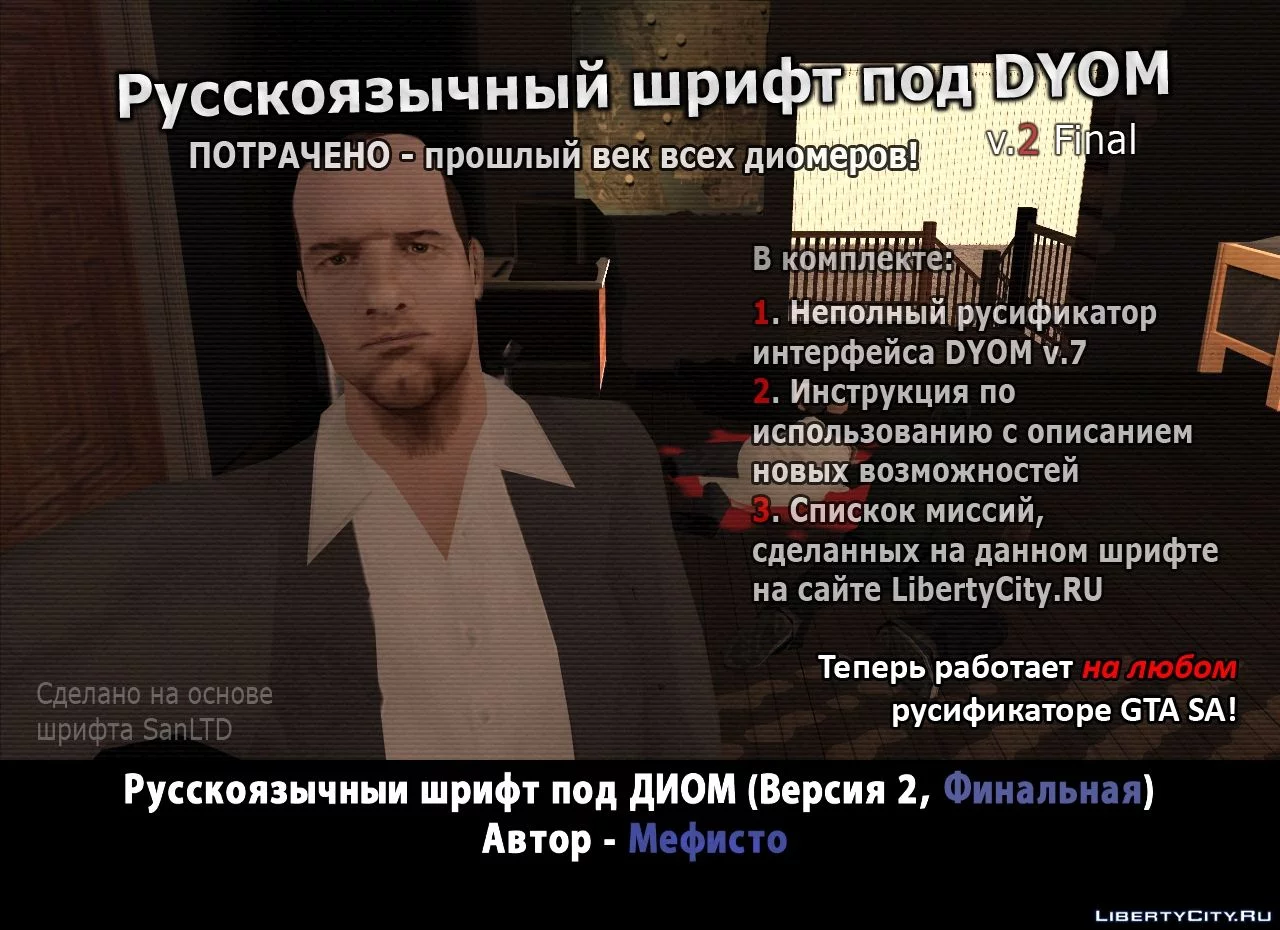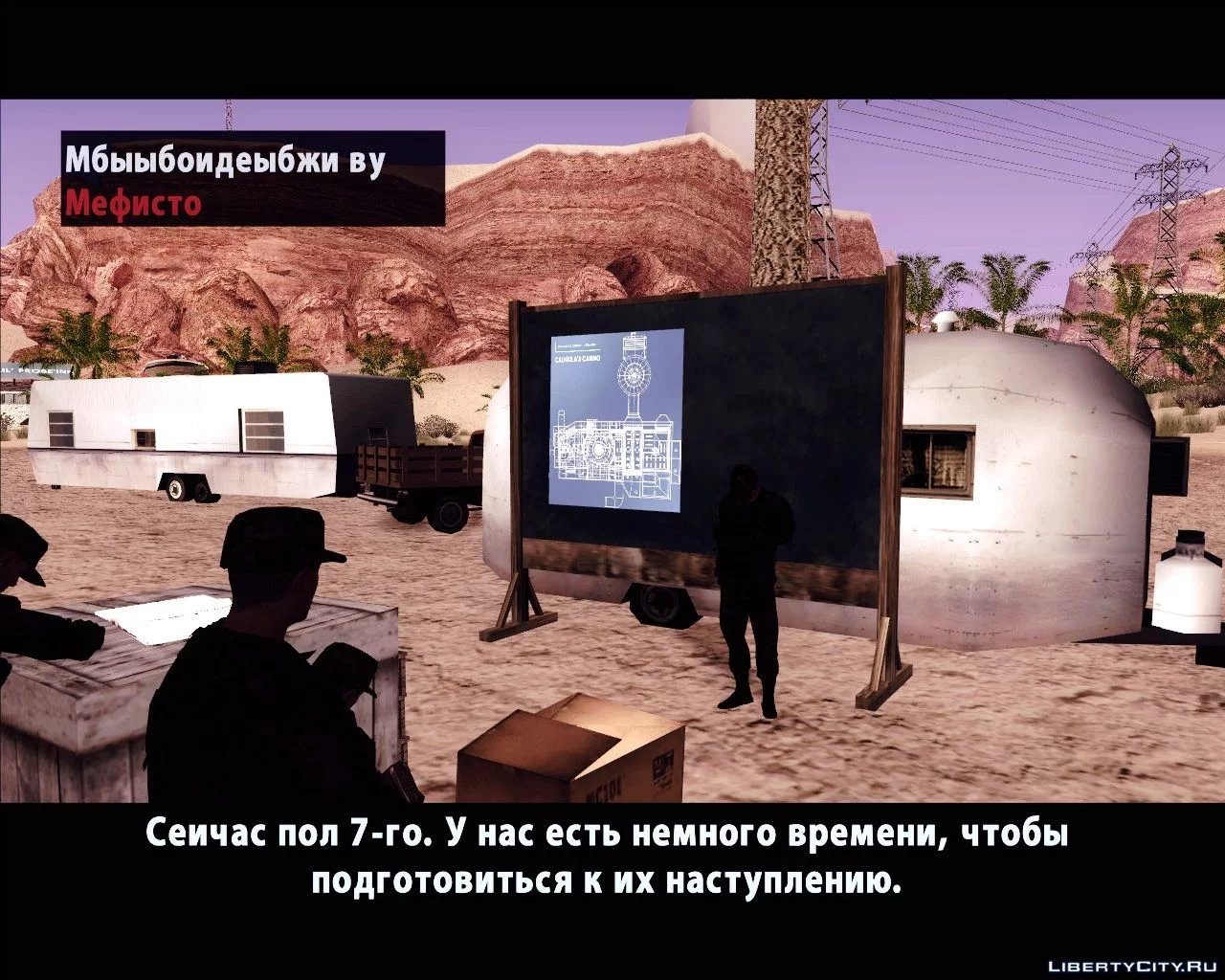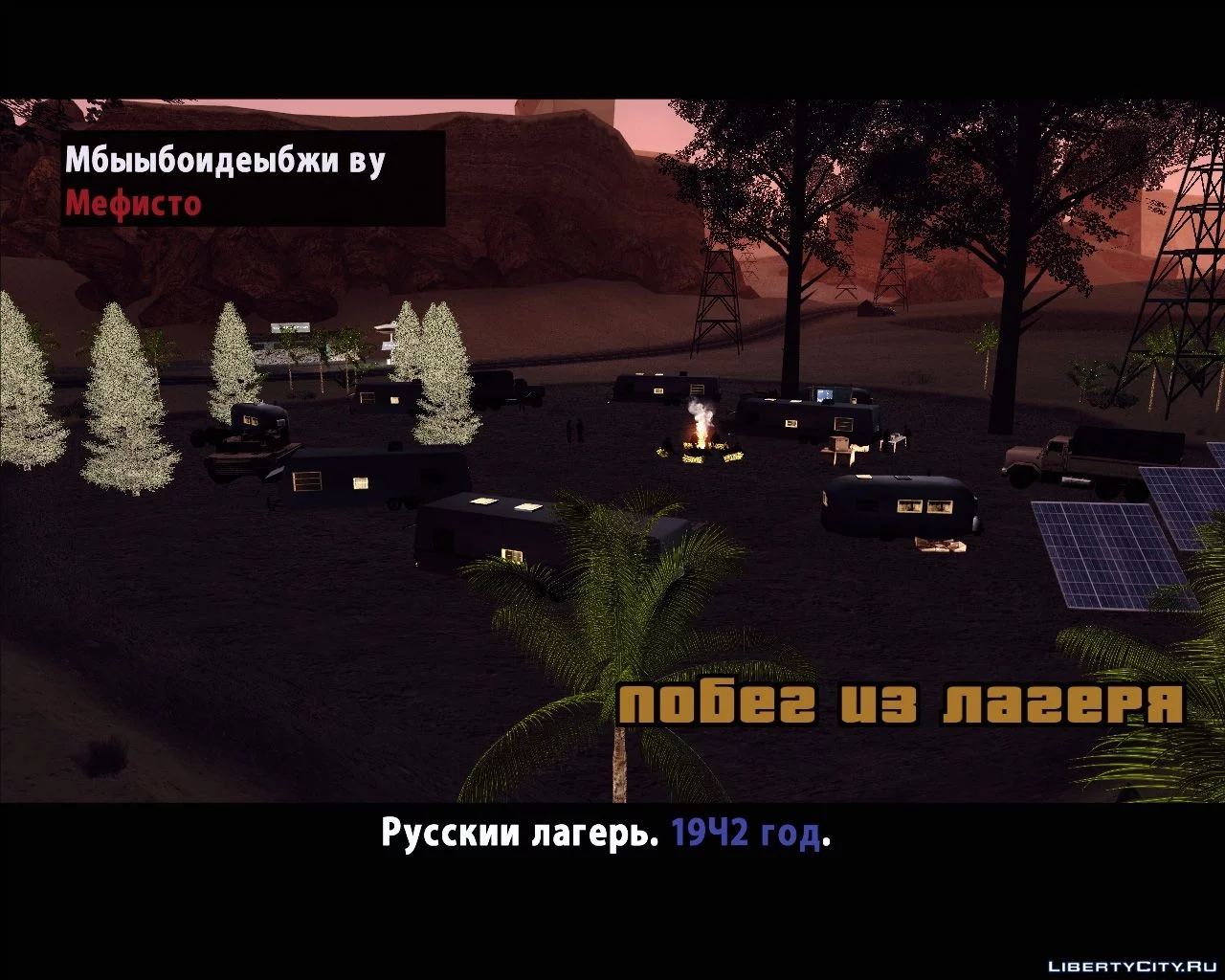
Русскоязычный шрифт для DYOM v.2 (FINAL)
ПОТРАЧЕНО - прошлый век в диомерстве!
Вот и вышла вторая версия моего, наверное, самого успешного мода. Что же нового по сравнению с предыдущей версией?
1. Теперь поддерживаются ЛЮБЫЕ русификаторы для GTA SA!
Этот шрифт теперь идет как на ПОТРАЧЕННЫХ русификаторах, так и на русике от SanLTD.
2. Новый шрифт.
Многие любят русификатор GTA SA от SanLTD, поэтому новая версия основана на шрифте именно
этого русификатора, а значит, не портит атмосферу игры.
3. Пофиксено большинство ошибок из первой версии.
Теперь в моде намного меньше багов, игра более комфортна. Но не смотря на это, шрифт все равно пригоден для использования исключительно в DYOM. В самой сюжетной игре SA будут видны баги шрифта (но вылетов нет).